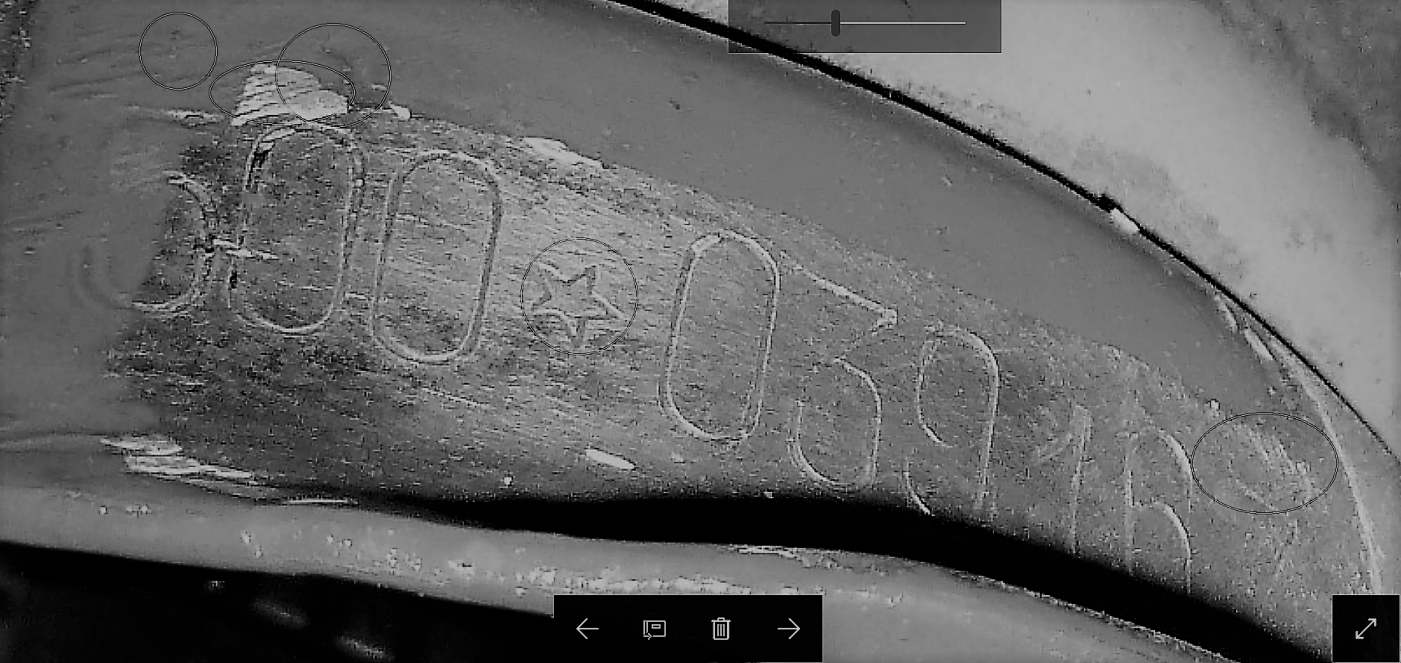
Wie alt ist dieser Schrifttyp
Für Maschinengravuren oder Schlagzahlen werden keine Schriftarten verwendet, wie wir sie vom Buchdruck oder digital kennen, sondern das sind von jedem Hersteller eigens kreierte, die sich oft nach rein technischen Gegebenheiten richten: Unterscheidbarkeit, gleichmäßiger Druck, gleichmäßige Abnutzung, große Auflagefläche, wenig Verkanten und so weiter.